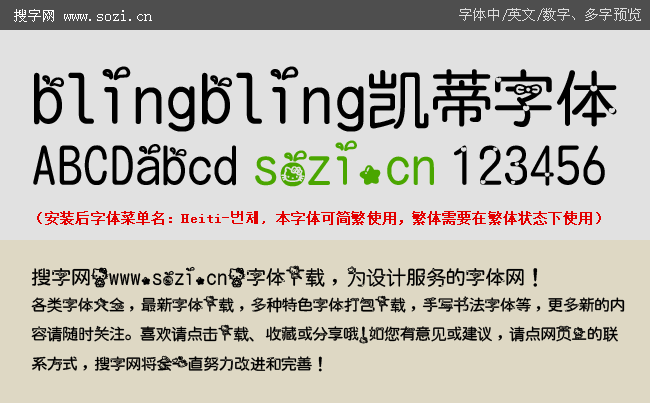
blingbling凱蒂字體
搜字網(wǎng)給大家提供一款很有趣的手機(jī)中文字體下載。修改者給他起名為blingbling凱蒂字體,這款手機(jī)字體是在中圓體字體筆畫間插入了可愛的卡通圖案。在具備中圓字體醒目清晰端正的風(fēng)格同時(shí),卡通味也特別濃,是一款非?蓯鄣目ㄍㄗ煮w,特別適合喜歡手機(jī)字體個(gè)性一些的朋友在手機(jī)上安裝使用。